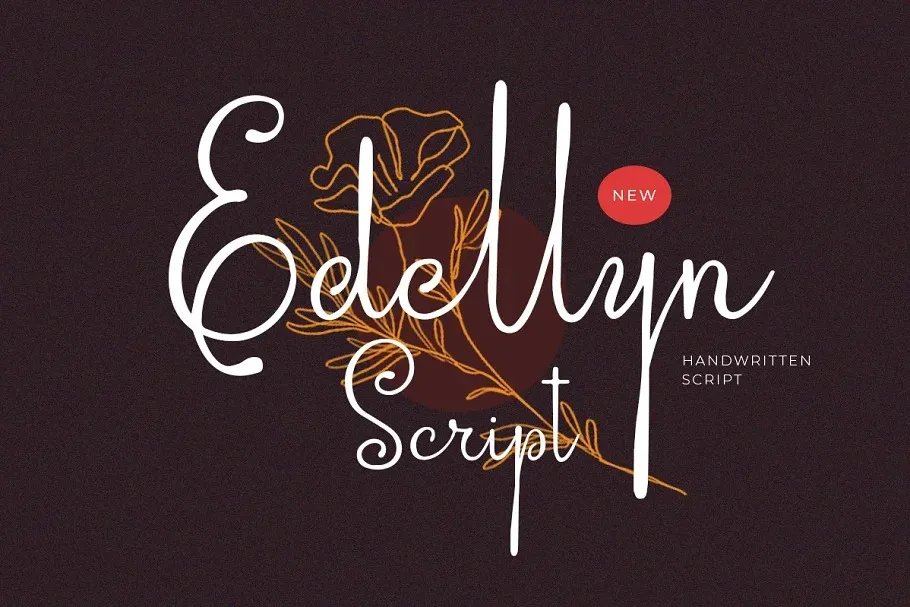
Edellyn Font – Download Grátis
A fonte Edellyn é uma escolha perfeita para quem busca um estilo elegante e casual ao mesmo tempo. Desenvolvida pela Littlehand, essa font foi criada para oferecer letras distintas e equilibradas que se destacam no mundo da tipografia moderna. Este tipo de letra é ideal para personal branding, tendo a capacidade de ser aplicada em diversas formas: desde logotipos, roupas e cartões de convite até embalagens e materiais publicitários. Sua beleza e simplicidade permitem que seja usada de forma elegante e contemporânea em diversos ambientes, tornando-a uma opção confiável para designers buscando um estilo único e moderno. Edellyn é a escolha certa para quem busca expressar sua personalidade através do design de fontes.